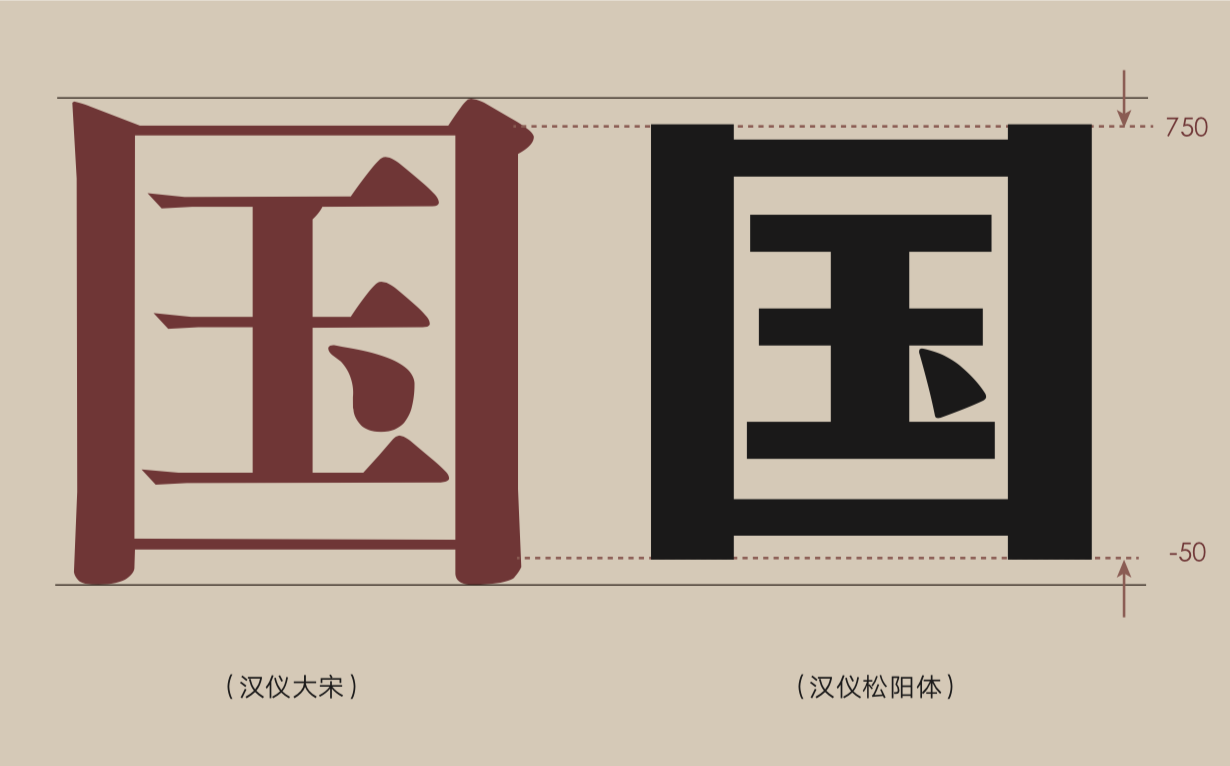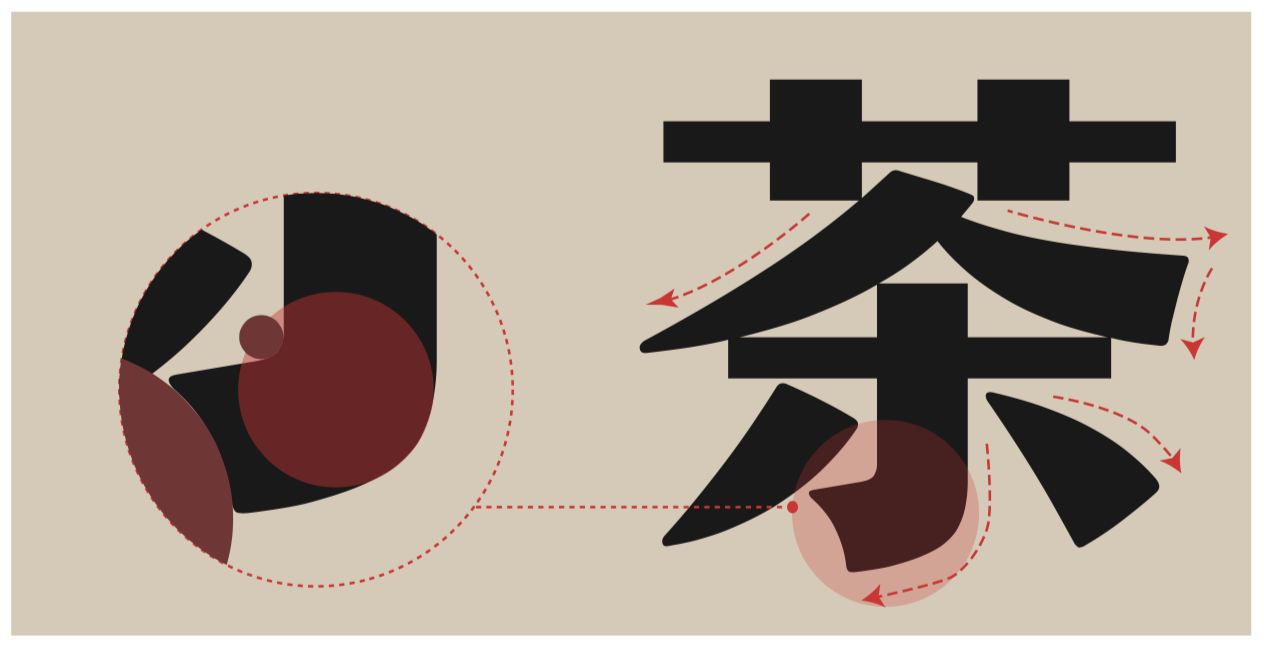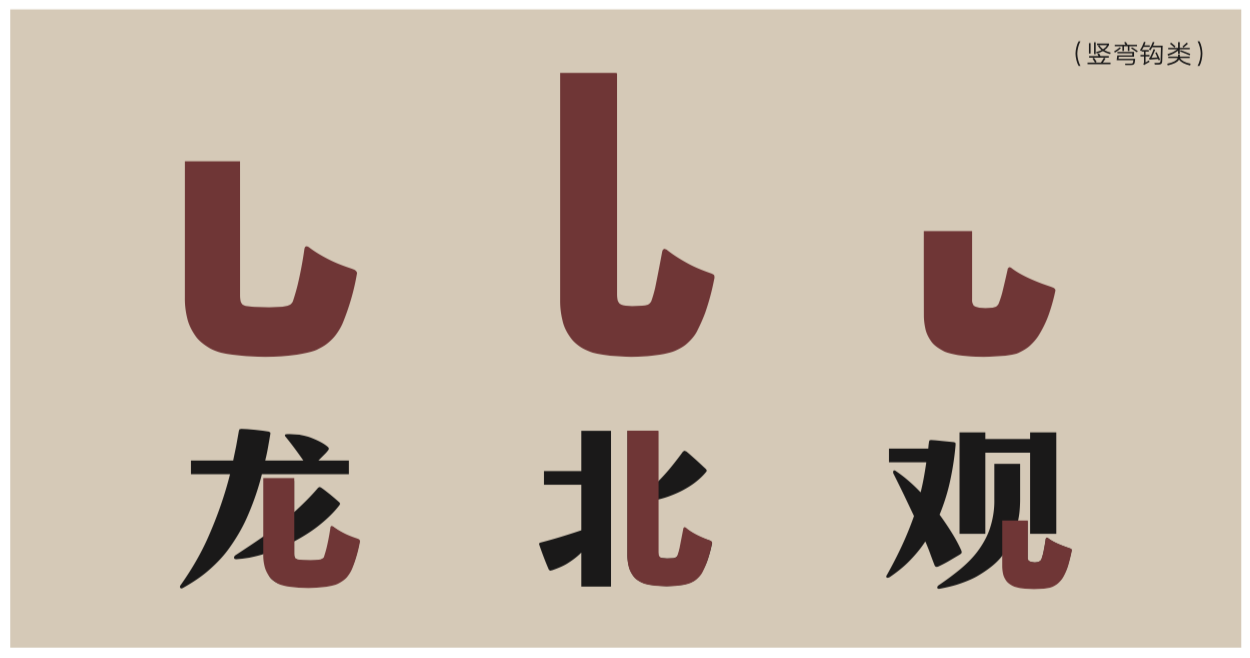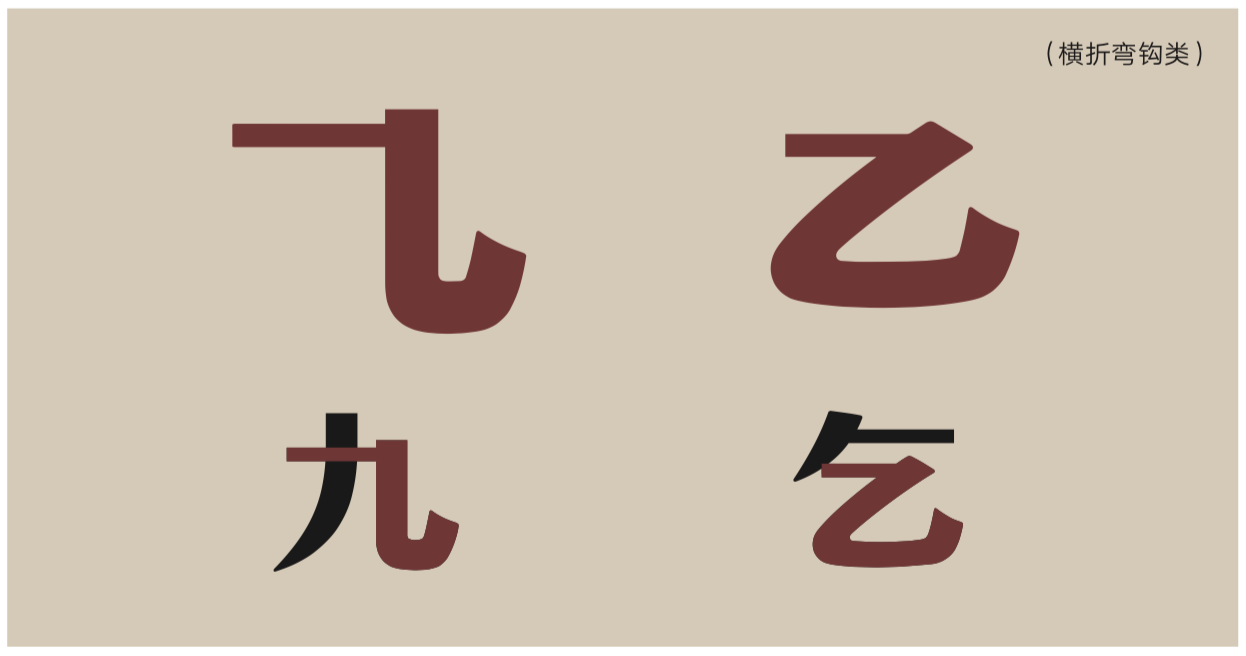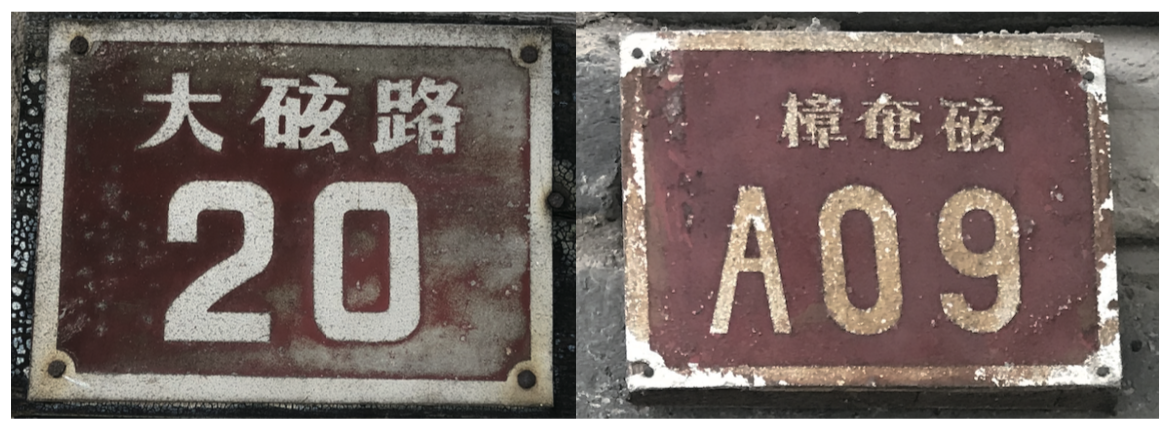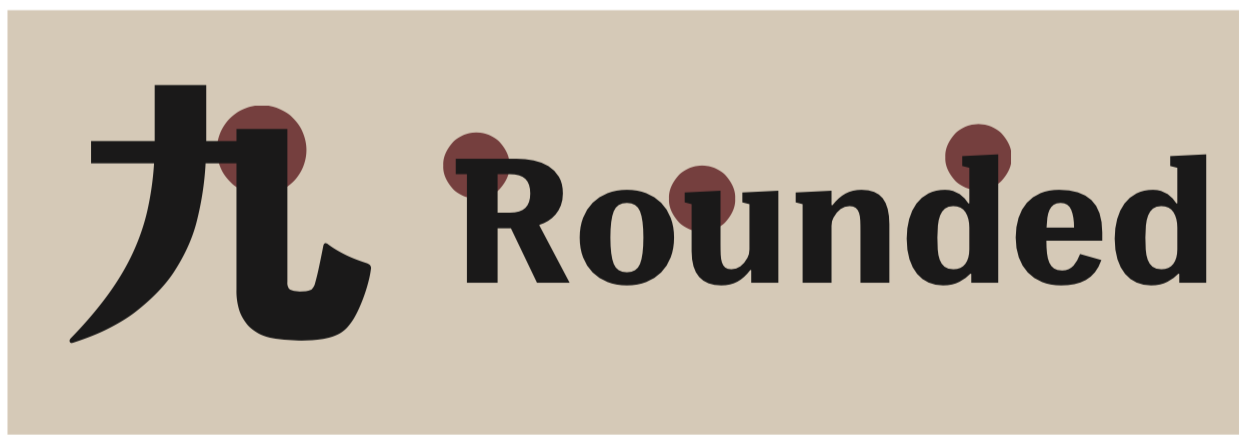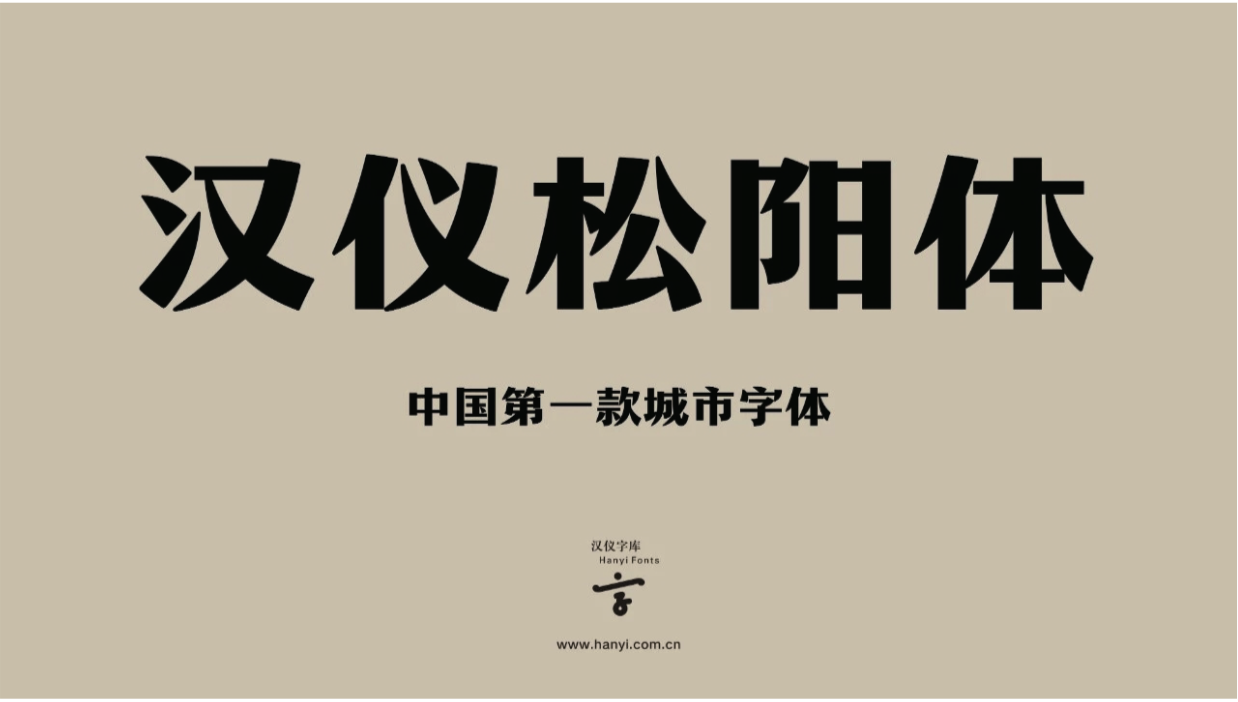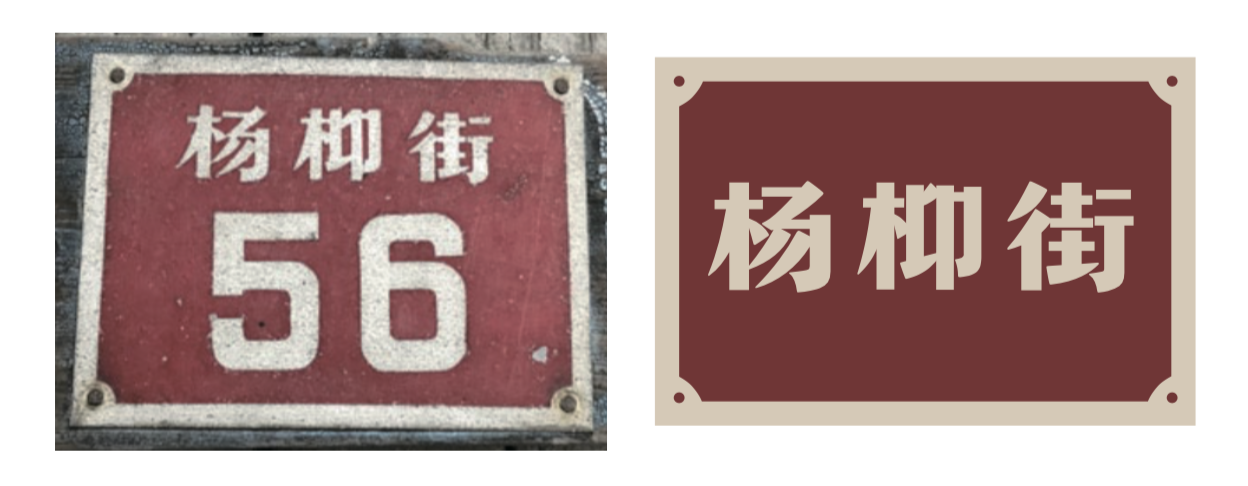
汉仪松阳体 | 城市字体
“汉仪松阳体”作为中国首款城市字体,是由著名设计师吴勇&汉仪字库高级字体设计师刘宇共同设计,经汉仪字库艺术顾问、著名字体设计师朱志伟指导,在松阳县政府的支持下完成的。
文字是文化的基因,城市文字也在以它自己的方式记录着你所看不到的城市故事,传承着千百年不息的人文精神。曾经,几乎中国的每一个城市都有其门牌字体。从老上海、北京、南京、广州到各个市县行政区,各自制作,因此百花齐放,各有特色。
如今,千篇一律的街牌布满了全国,上面的字体是毫无温度的通俗字体。我们越发怀念这些老旧的字样,它们源于 " 秀才 " 们一笔一画端端正正的书写,蕴含了每条街道、每户人家内心最朴实美好的心愿。它们那么美,如今在时代的洪流中却似是不曾来过。
松阳字体是一款承载着松阳优秀基因的字体,它早已与松阳古建筑融为一体。虽然我们已无法考证其出处,但在松阳遗留下来的它,依然神采奕奕。这款字样曾经风靡一时,在很多地方都有自己的同胞兄弟,但因为没有做数字化的统一,且作者的书写习惯各自不同,故存在差异。而松阳这款字体,在具备相似风格的同时,也极具自己的特色。
现在,松阳老城区仍保留了一部分这样的具备历史价值的门牌字样,使人们能够感受到这些字体的年代感。这些门牌字体的结构中有一种随意变化而有趣的质朴美感,让我们意识到它的人文价值所在,它们早已和松阳城的街道建筑融为一体,成为独一无二的松阳品味。
我们通过对松阳门牌字体的整理和再设计,得到了“汉仪松阳体”。这款字体在结构上提炼了门牌字的特点,整体风格怀旧淳朴,有着老城区的质感。
汉仪松阳体 | 结构端正平和
字形方正呈扁式,稳重而有力。相对于常规宋体(例如汉仪大宋)而言,字身上下有收短。
“汉仪松阳体”是一款字面宽博、中宫微收、重心偏上的字体,其字面比例高达92%。这款字体设计的方正、均匀、饱满、挺拔,有一种直率硬朗的宋黑体味道,具有一定的标示性。
汉仪松阳体 | 笔画灵动质朴
“汉仪松阳体”的笔画设计保留了松阳街道小巷里门牌字样的字体感觉,与印刷字体平板僵直的感受不同,这款字体灵动质朴,有着原始手工质感和时间的烙印感。尤其是在撇、捺、钩、提的处理上,很有弹性、有精神。
“汉仪松阳体”的笔画粗细对比鲜明,空间结构布局合理。
汉仪松阳体 | 线条圆润饱满
“汉仪松阳体”的弯钩曲线饱满而富有力量,运用不同弧度的曲线来使笔画圆润但有力。
笔画钩的形态丰富多样,在表现笔画厚实、有弹性的基础上,根据不同的空间大小有不同的诠释。
汉仪松阳体 | 生僻字
“汉仪松阳体”除了常规字符集JFW外,还额外多出了三个生僻字,这是它的不同之处。
这三个生僻字来源于松阳县老街门牌和当地名人的姓名,是独属于那个时代的视觉记忆与文化表征。其中的“石玄”字,现时的字典和输入法中均未收录。如今我们将这些字收录在“汉仪松阳体”中,使它们能够继续在“松阳文化”中流传下去。
汉仪松阳体 | 西文字母
“汉仪松阳体”的西文字体与中文字体风格统一,有着相同的装饰衬线,字母粗细对比明显。
汉仪松阳体 | 排版效果